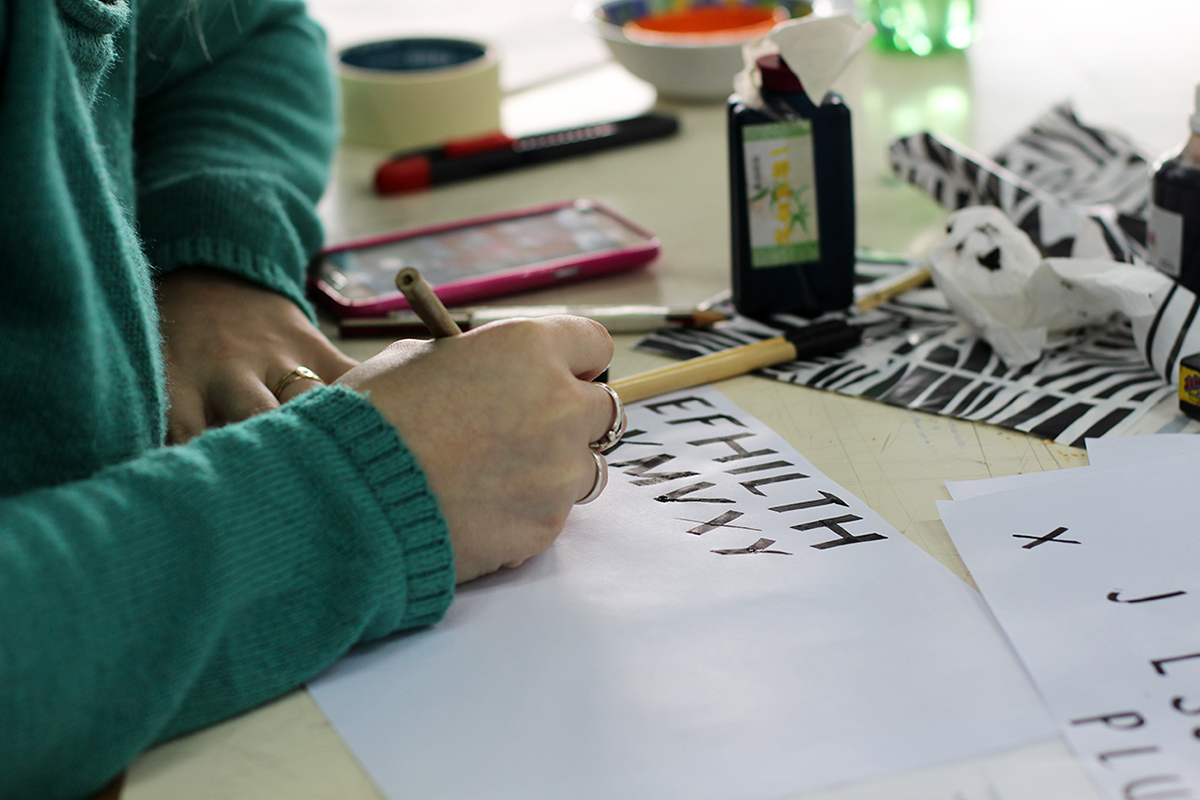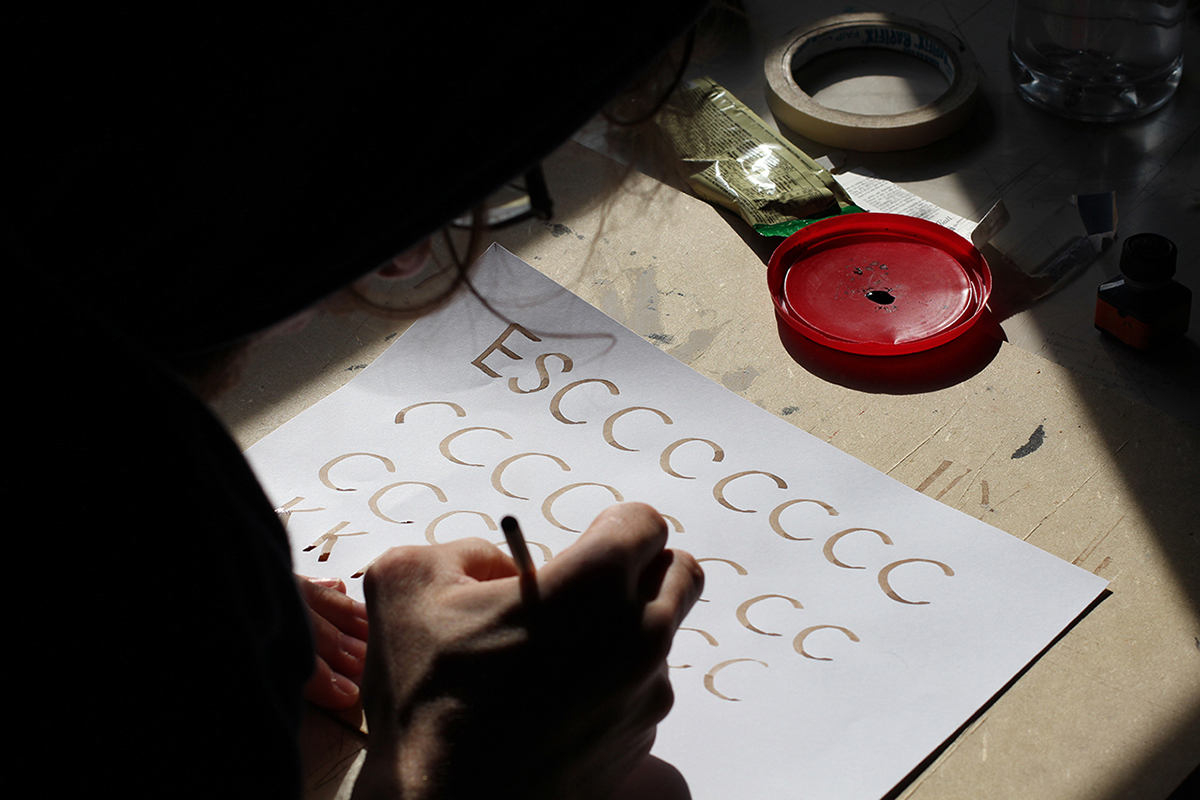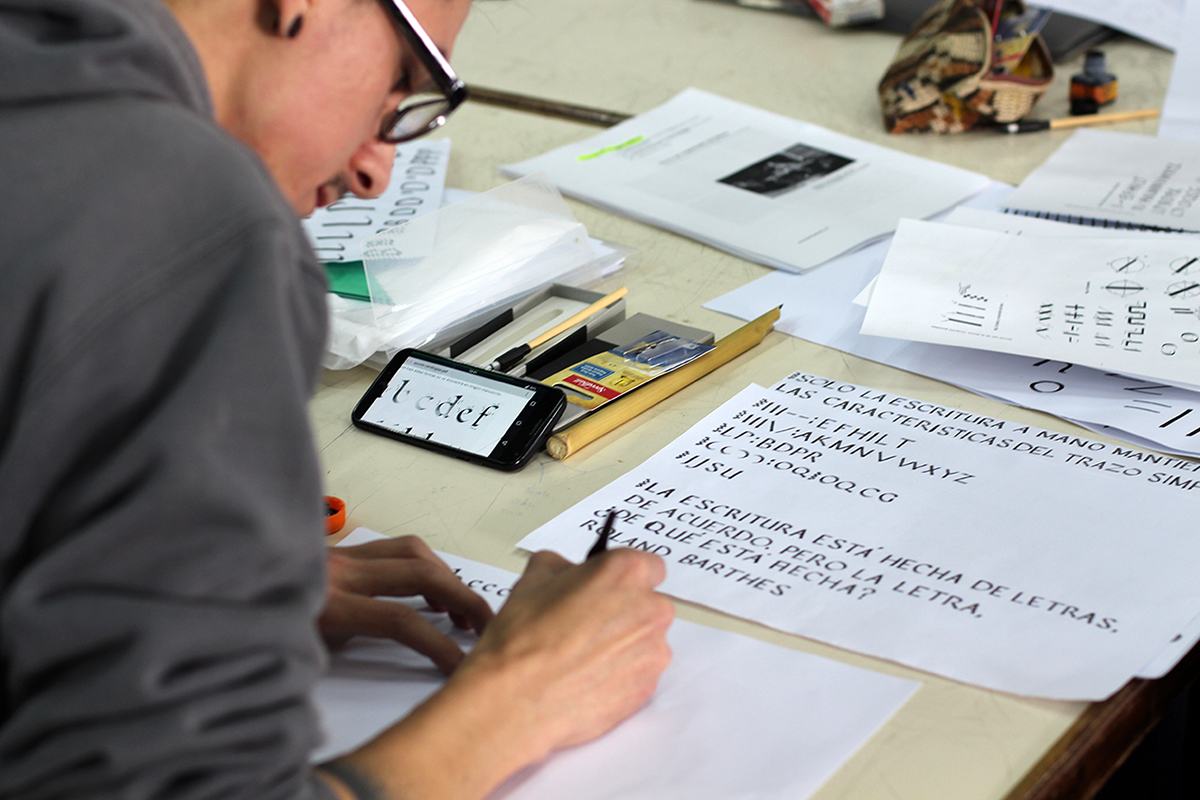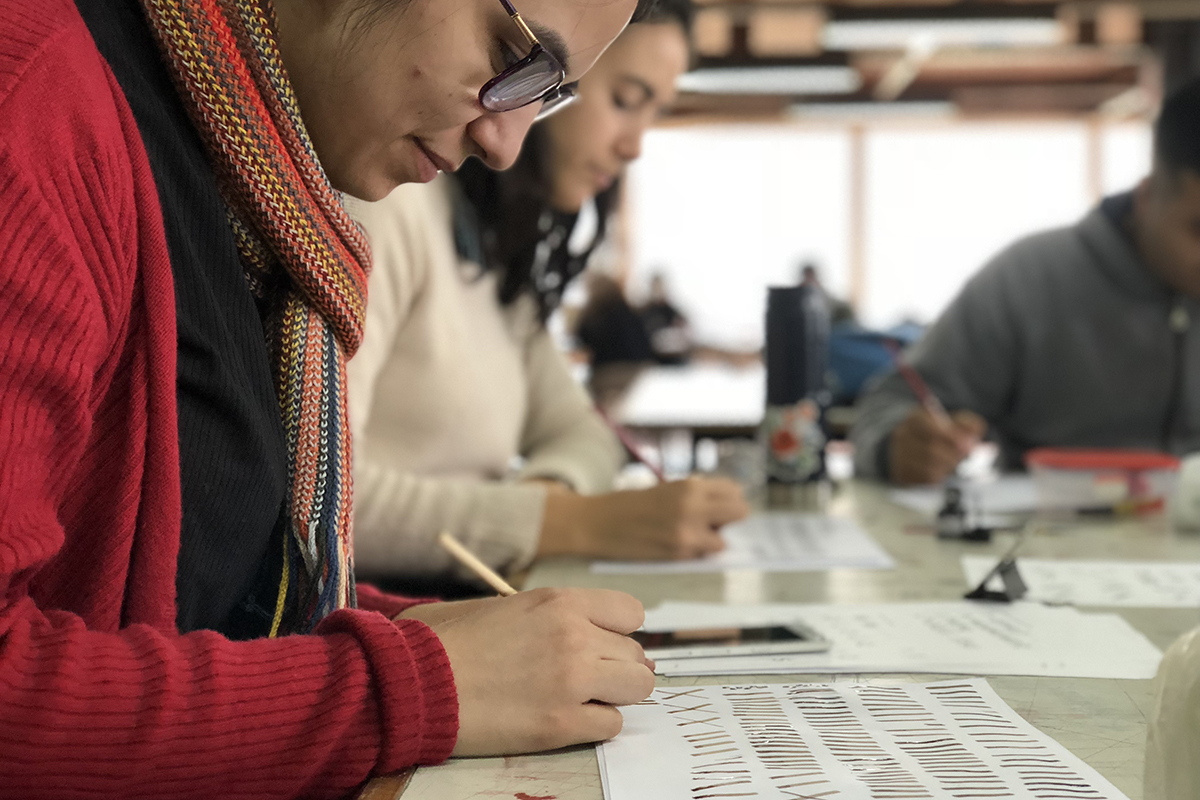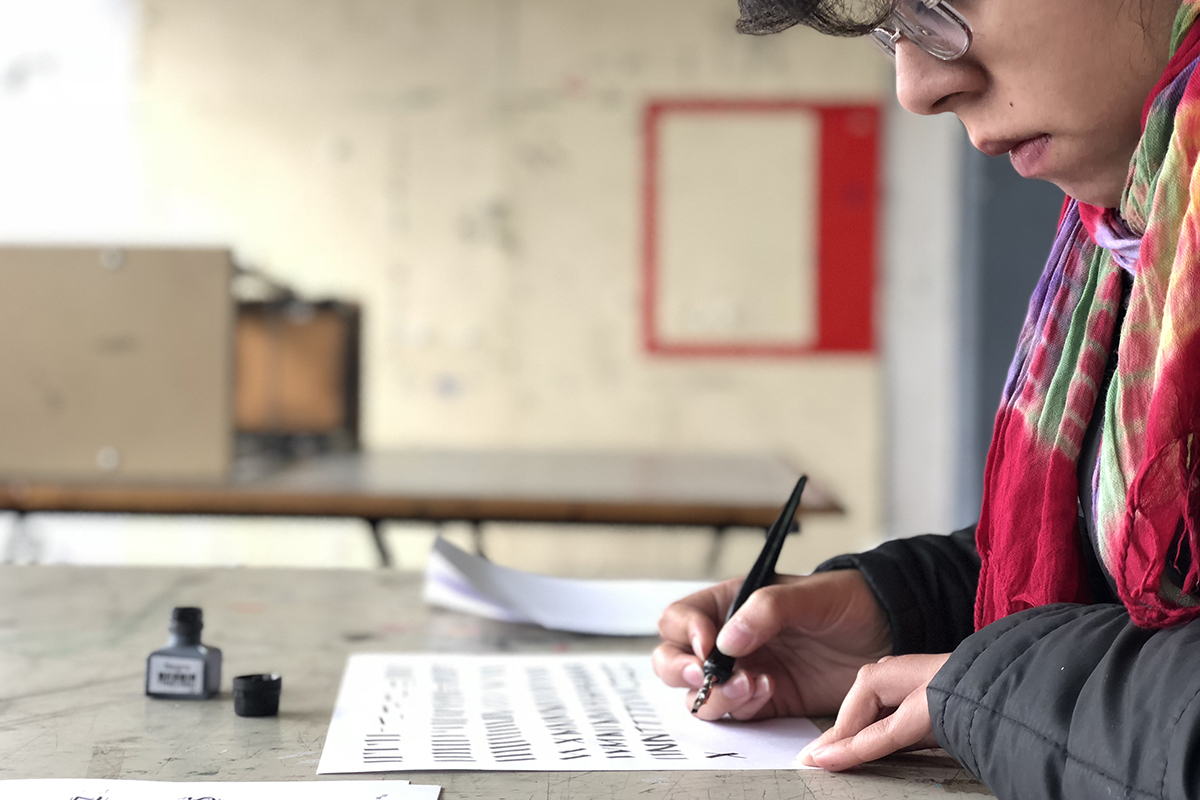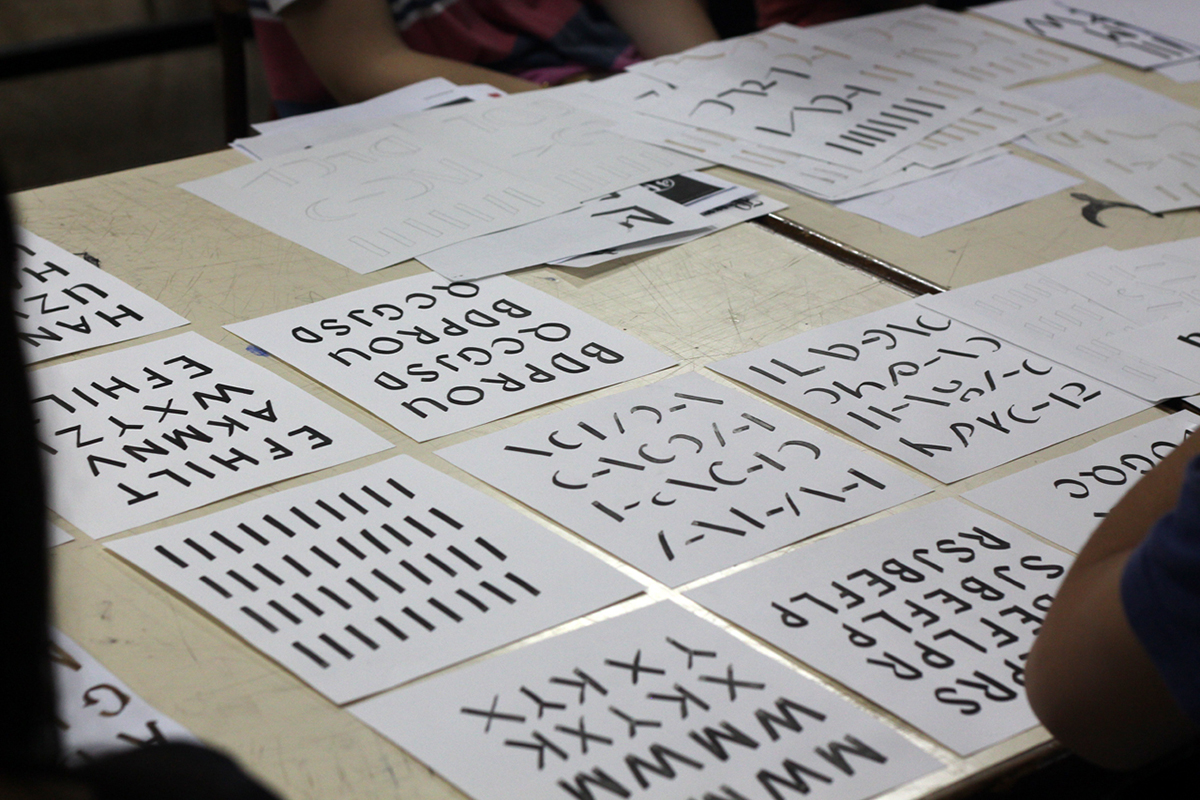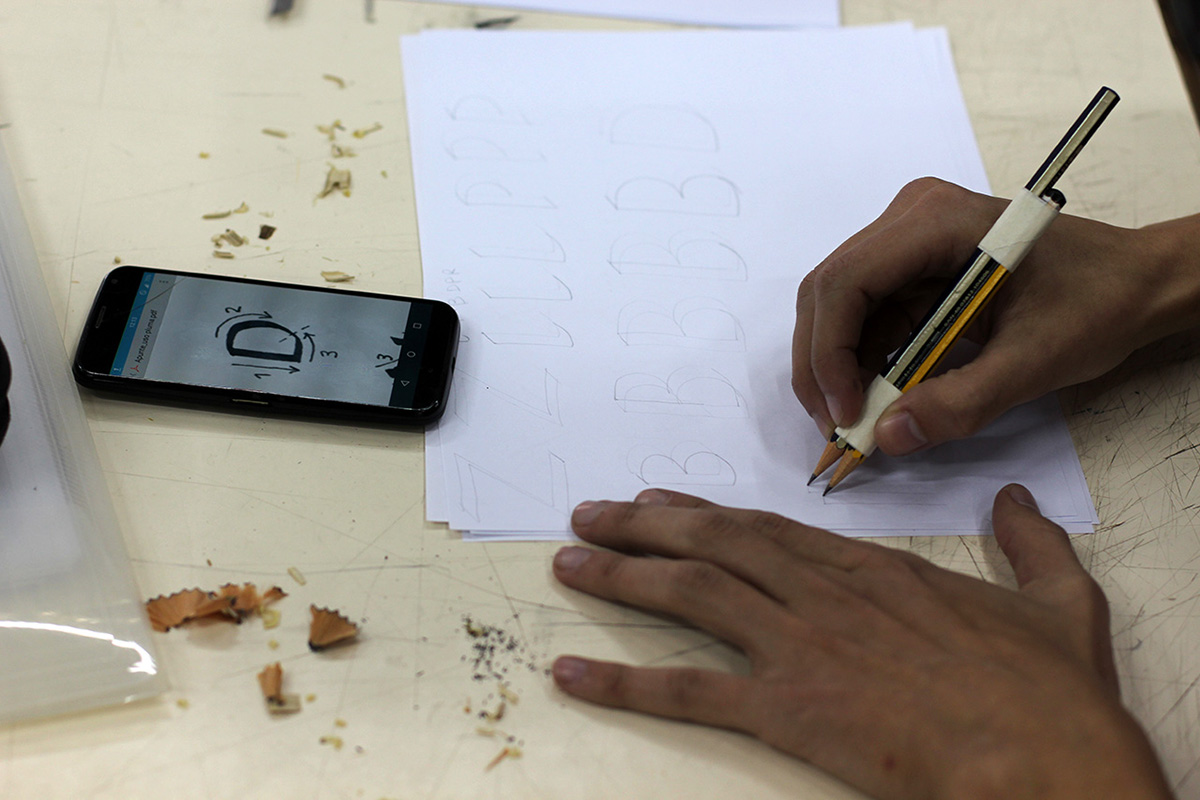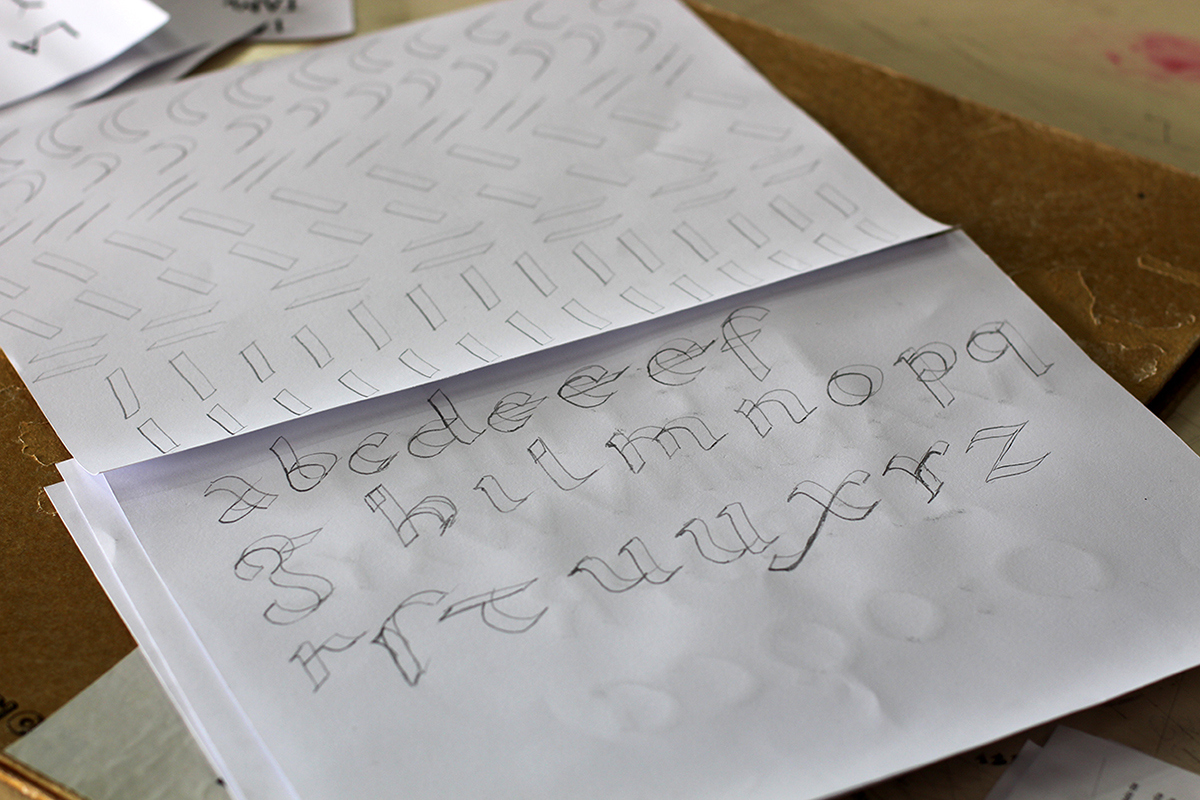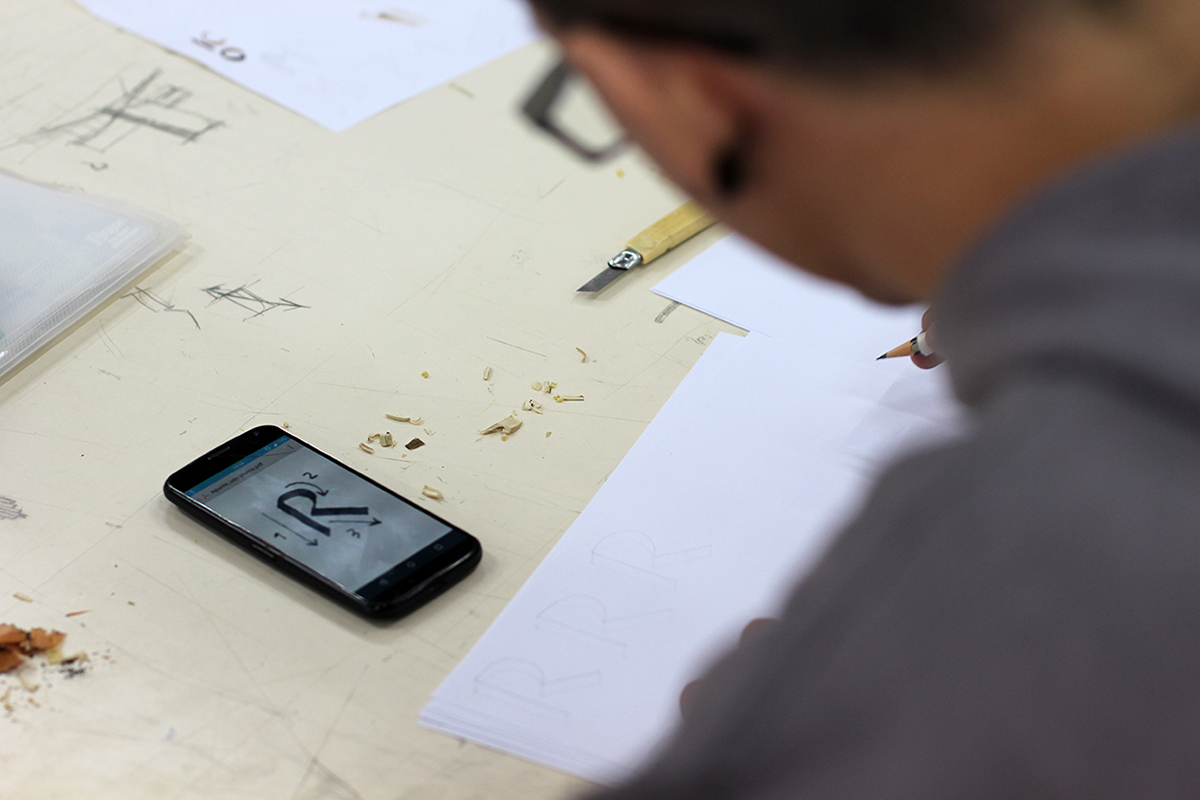
Signos alfabéticos / Uso de la pluma
Reconocimiento del signo
Este trabajo nos invita a comprender y sensibilizarnos con el trazo, ritmo y estructura de la letra en función del instrumento utilizado. Sus objetivos nos proponen lograr una articulación óptica y rítmica entre los distintos signos y comprender las identidades individuales como partes de un sistema homogéneo.